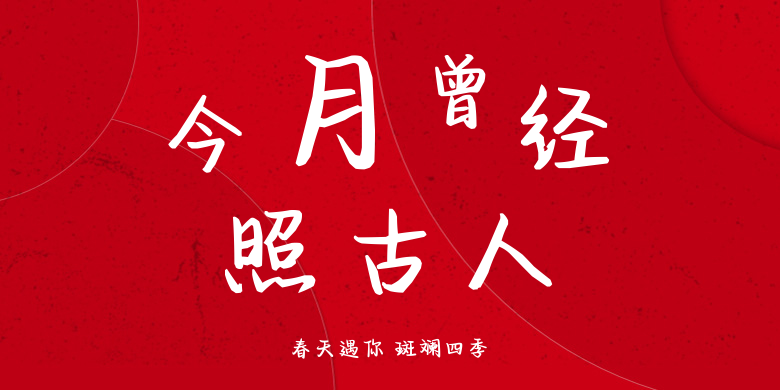
春天遇你 斑斓四季
春天遇你 斑斓四季,这款字体结构工整、笔画清晰,兼顾美观与易读性,适用于标题、正文、海报、包装、LOGO 等多种场景。字形优雅稳定,风格百搭耐看,适配日常排版与创意设计,让文字呈现更舒适、更具质感。春天遇你 斑斓四季一笔一画,皆是细节,以均衡的比例、流畅的线条打造舒适视觉体验,字形端正大气,风格简约现代。无论是商业设计、品牌宣传还是日常排版,都能轻松驾驭,让文字更有格调与力量。春天遇你 斑斓四季字体下载。